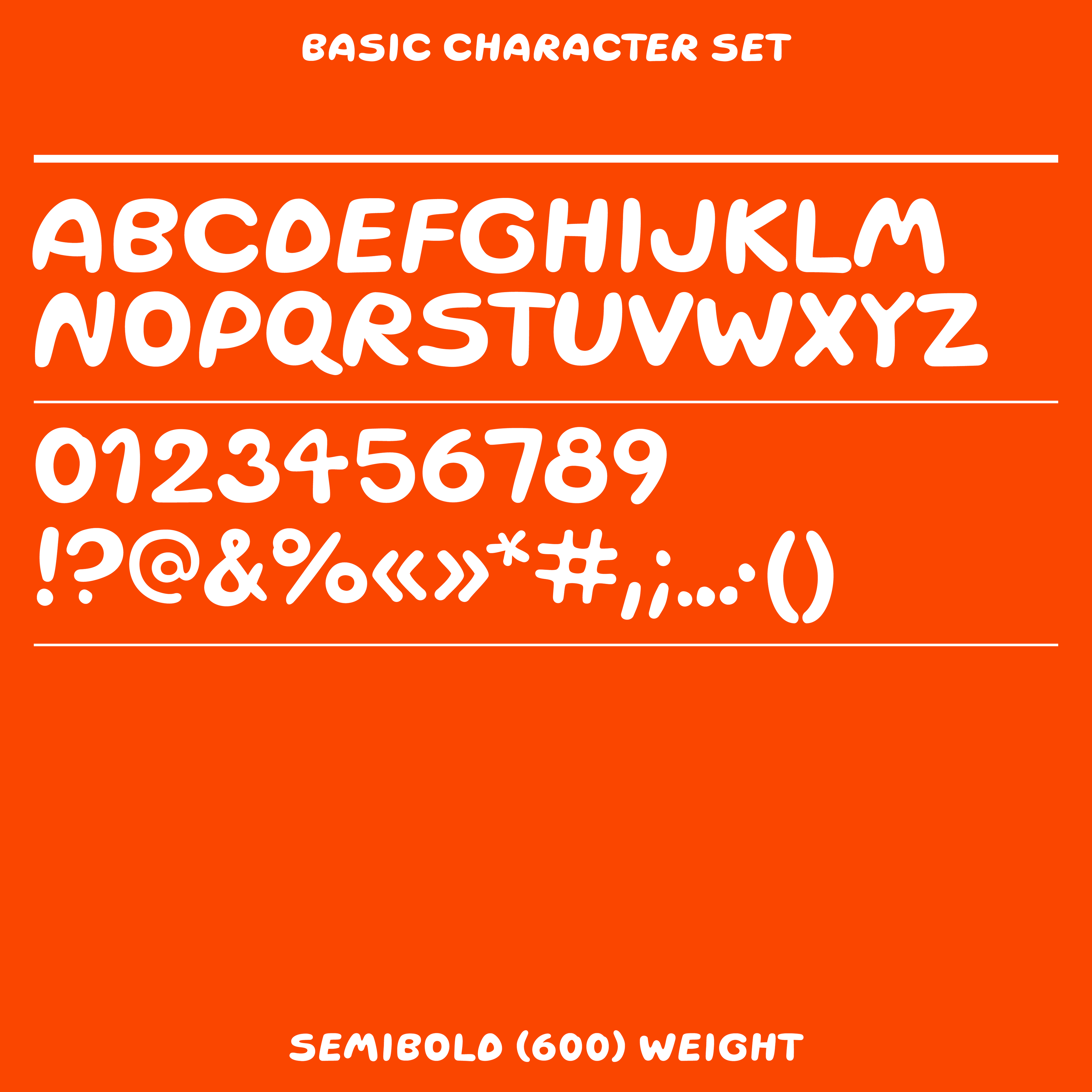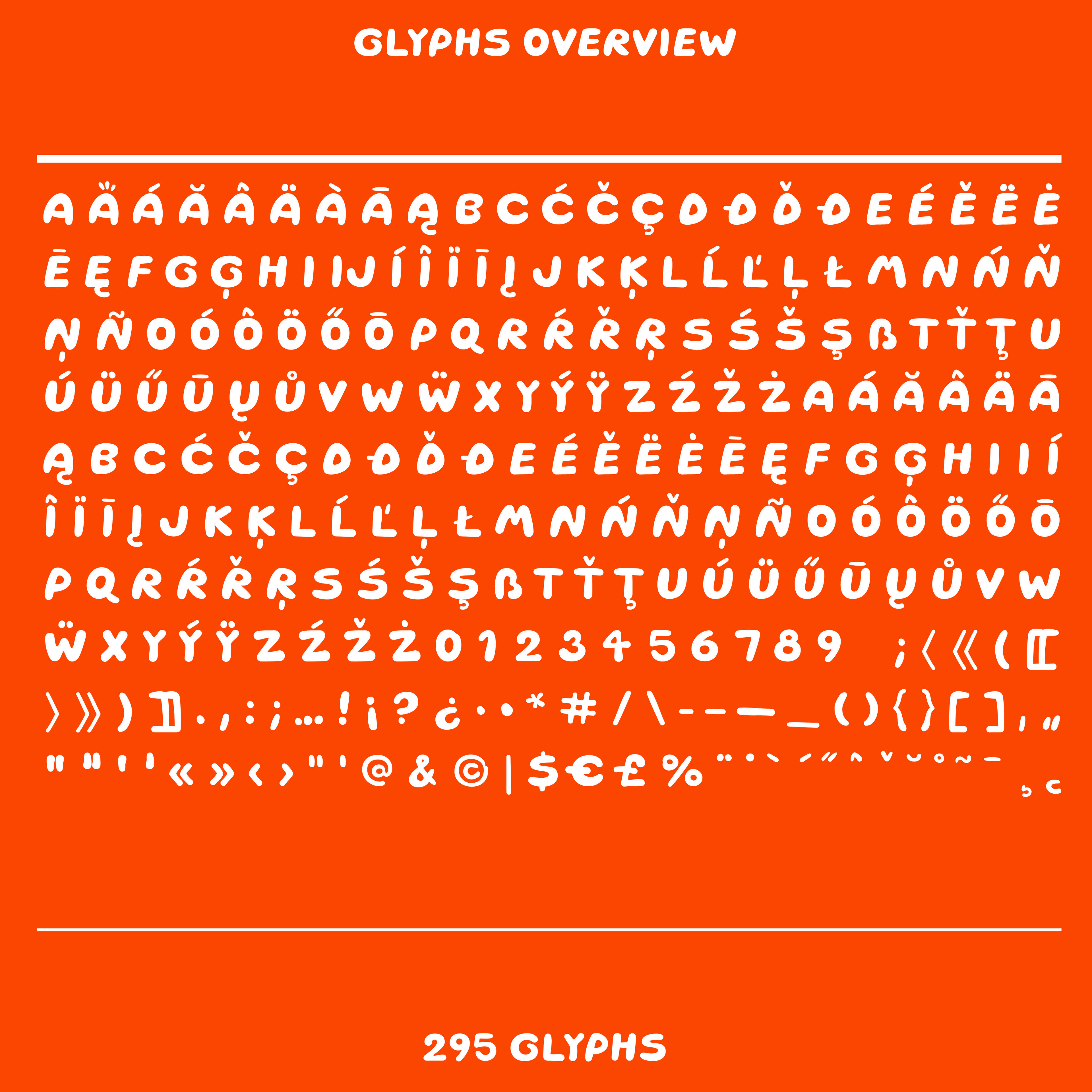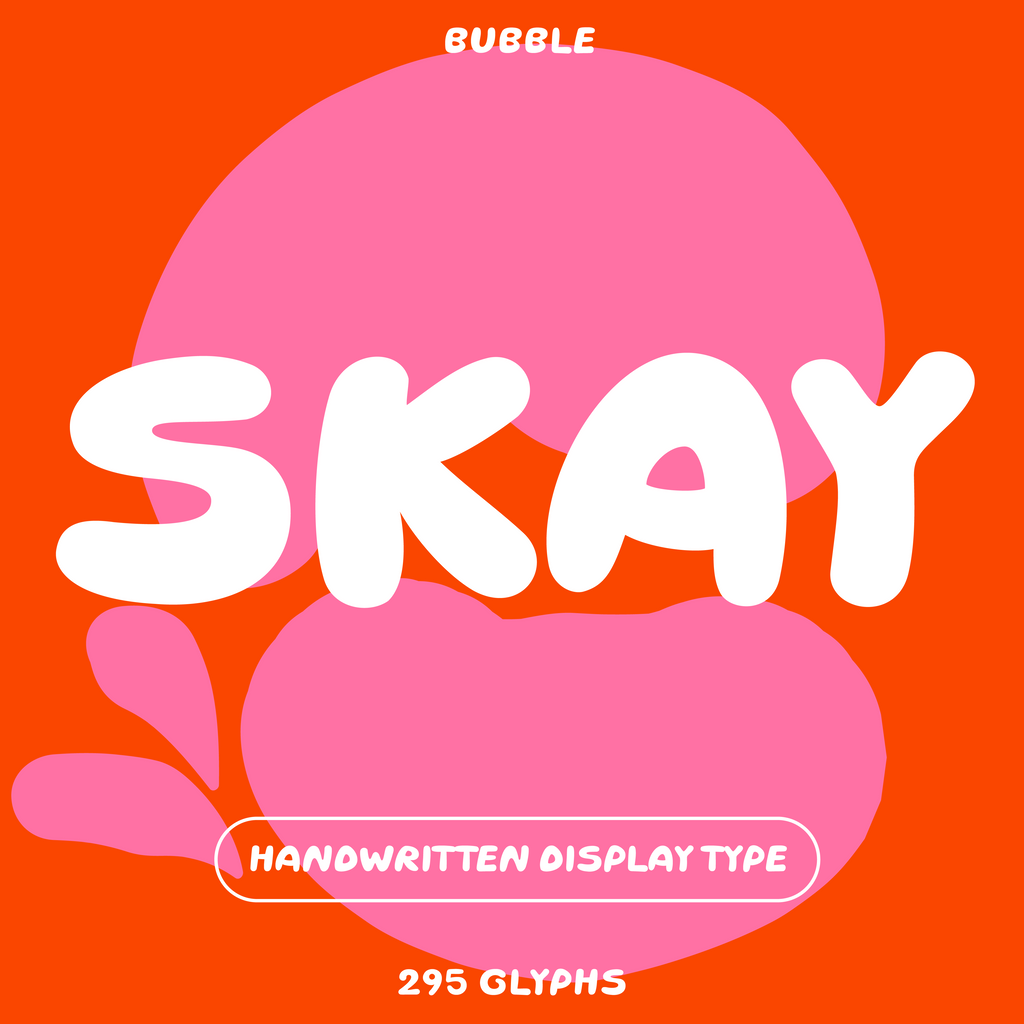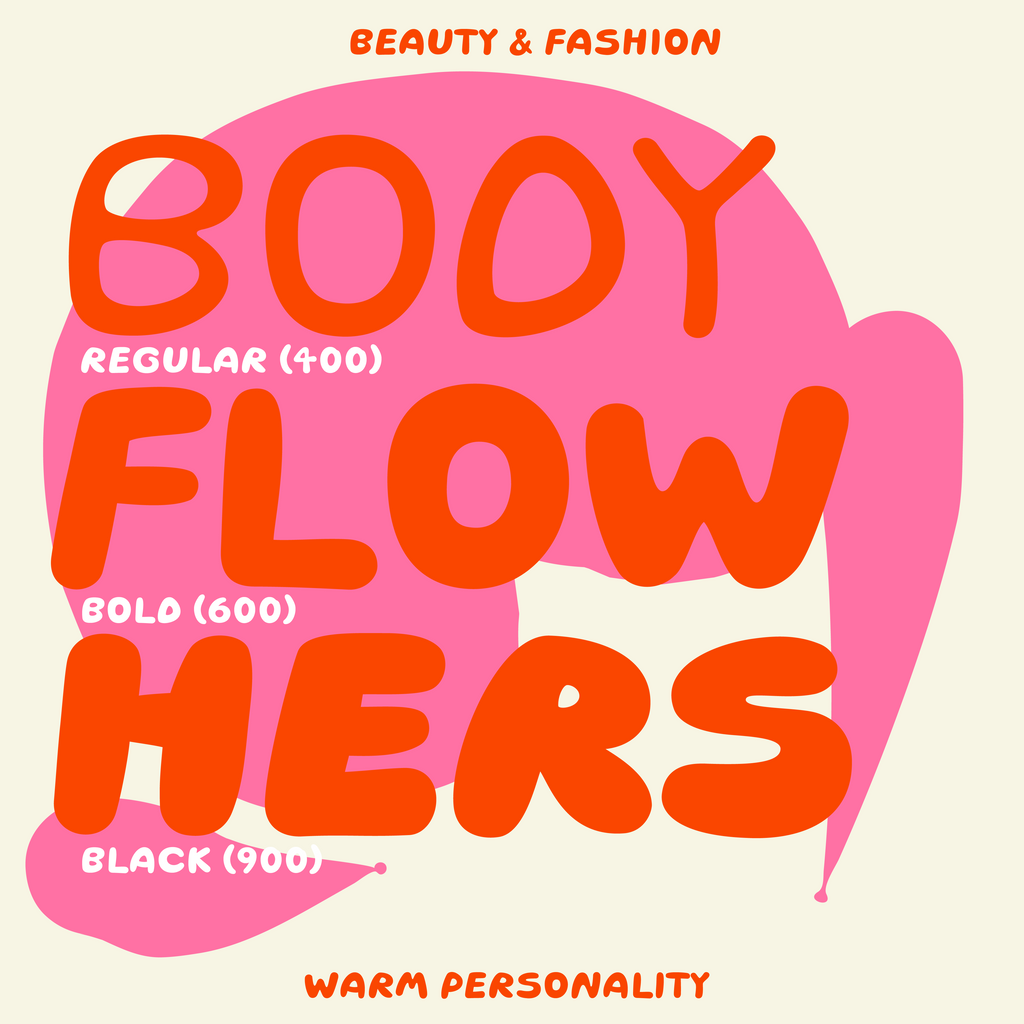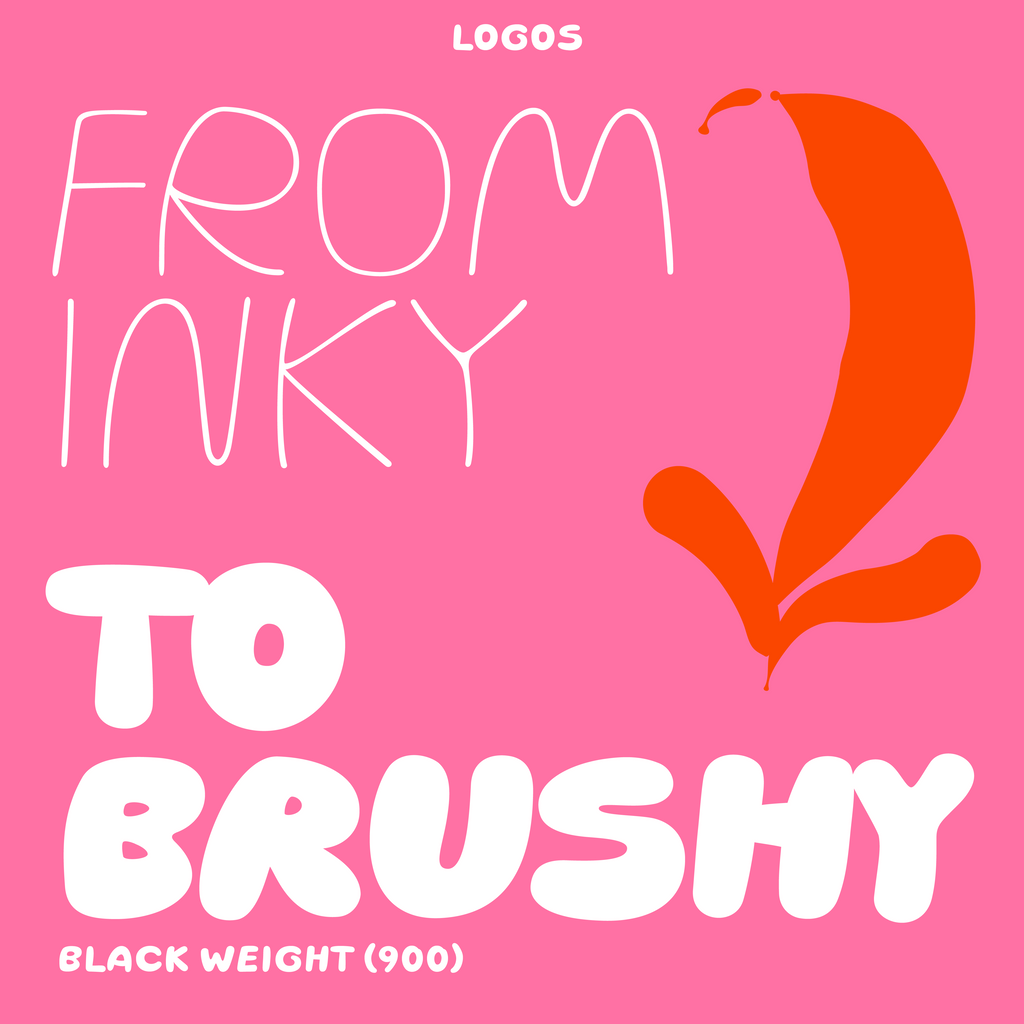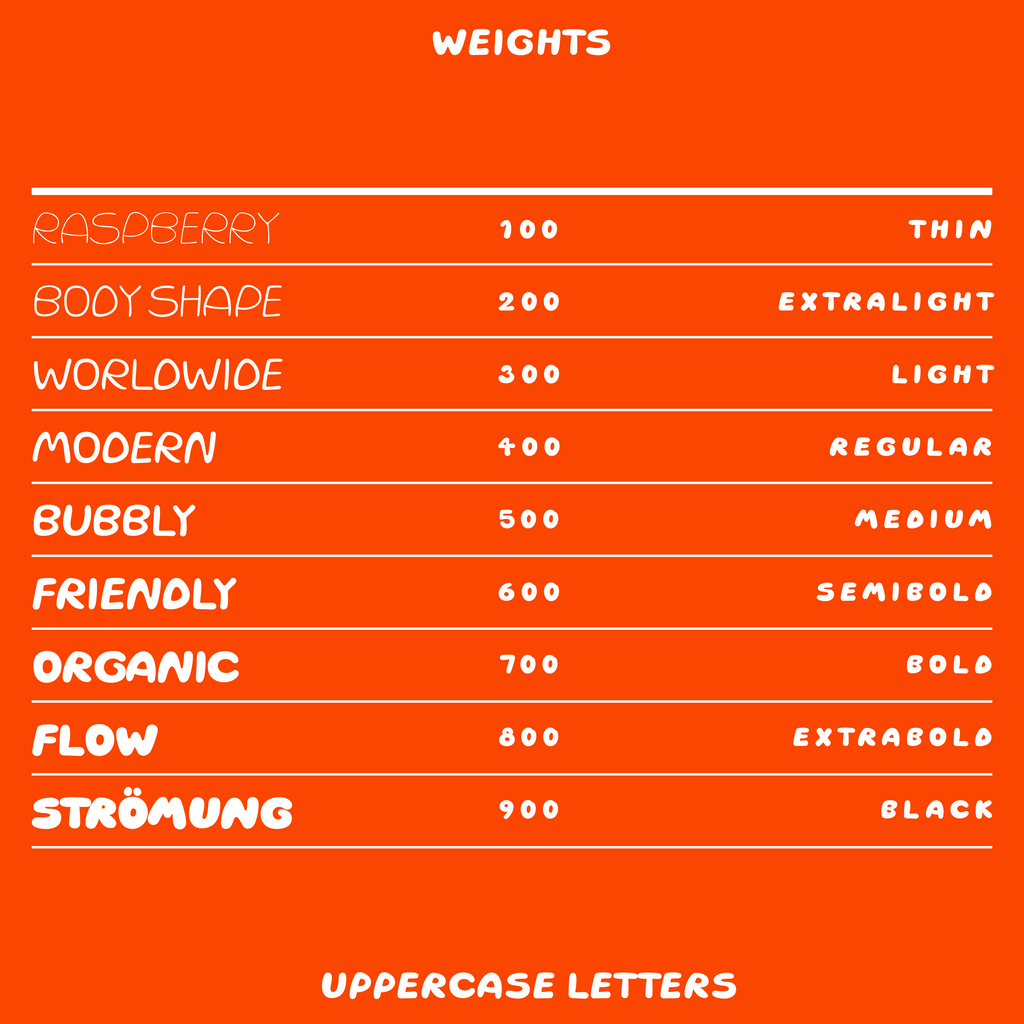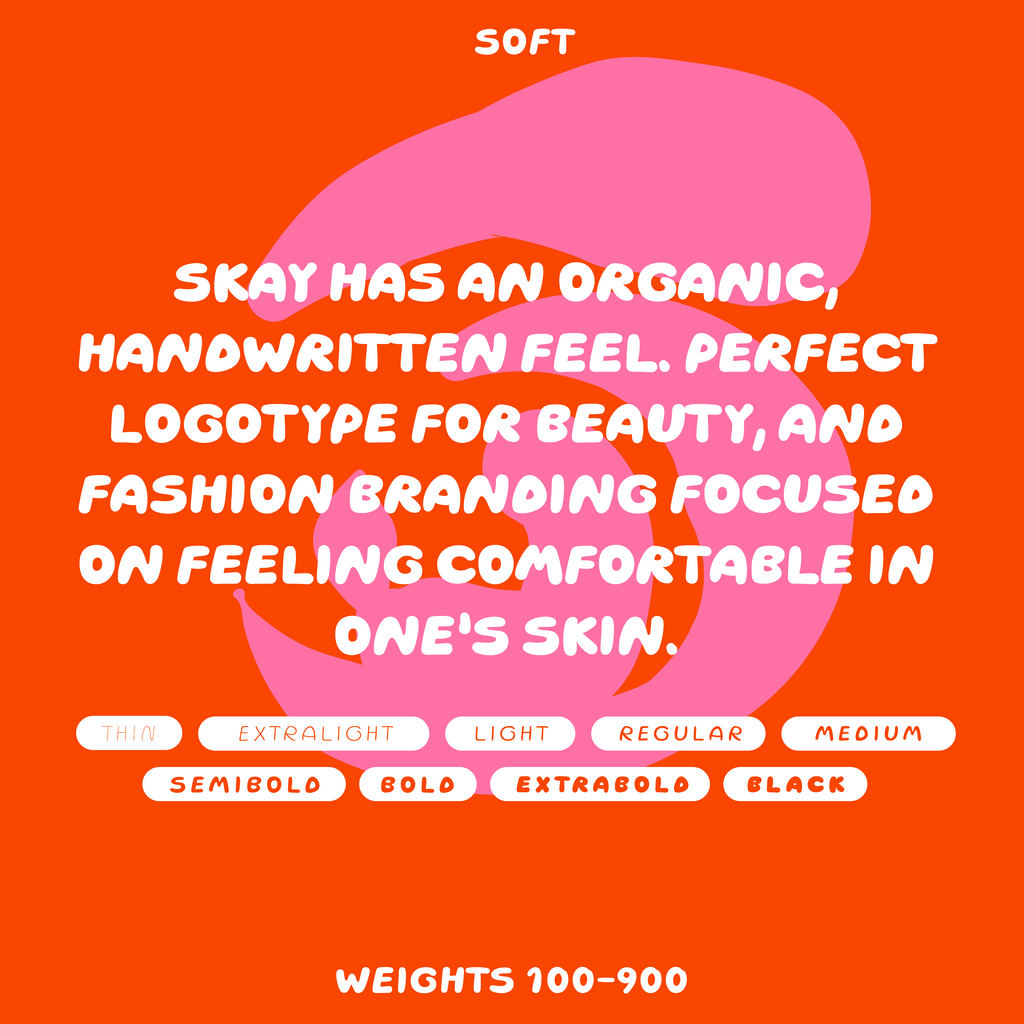
Skay ist eine organische, handgeschriebene Schriftart mit einem tintenartigen Strich in dünneren Schnitten und breitem Pinselstrich in fetteren Schnitten. Gut für Beauty- und Modemarken geeignet, bei denen das Wohlfühlen in der eigenen Haut im Mittelpunkt steht. Stilistisch ähnlich der Skims-Logoschriftart.
Skay – Handgeschriebene Bubble-Schrift für Beauty & Fashion